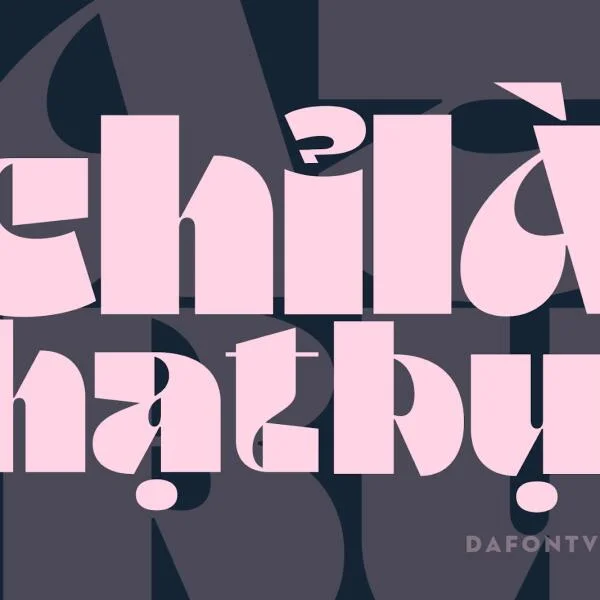
Tải Font Broad Việt Hóa - Phông chữ rộng hiện đại
Tổng quan về Font Broad
Font Việt Hóa Broad là một phông chữ Sans Serif với thiết kế độ rộng của từng chữ hiện đại hoàn hảo để sử dụng cho văn bản hiển thị, bạn có tận dụng kiểu chữ này cho các thiết kế sản phẩm, tiêu đề, banner quảng cáo, các text lớn...
BROAD - Modern Width Display Font
Mẫu 1
Font Việt Hóa Broad
Mẫu 2
Font BROAD - Modern Width Display Việt Hóa
Mẫu 3
BROAD - Modern Width Display Font việt hóa
Mẫu 4
Chi tiết ký tự của Font Broad
BROAD - Modern Width Display Font - Font việt hóa đầy đủ, kerning, chỉnh sửa và tối ưu lại 1 chút so với font gốc.
BROAD - Modern Width Display Uppercase
Chi tiết ký tự 1
BROAD - Modern Width Display Lowercase
Chi tiết ký tự 2
BROAD - Modern Width Display Number & Punctuation
Chi tiết ký tự 3